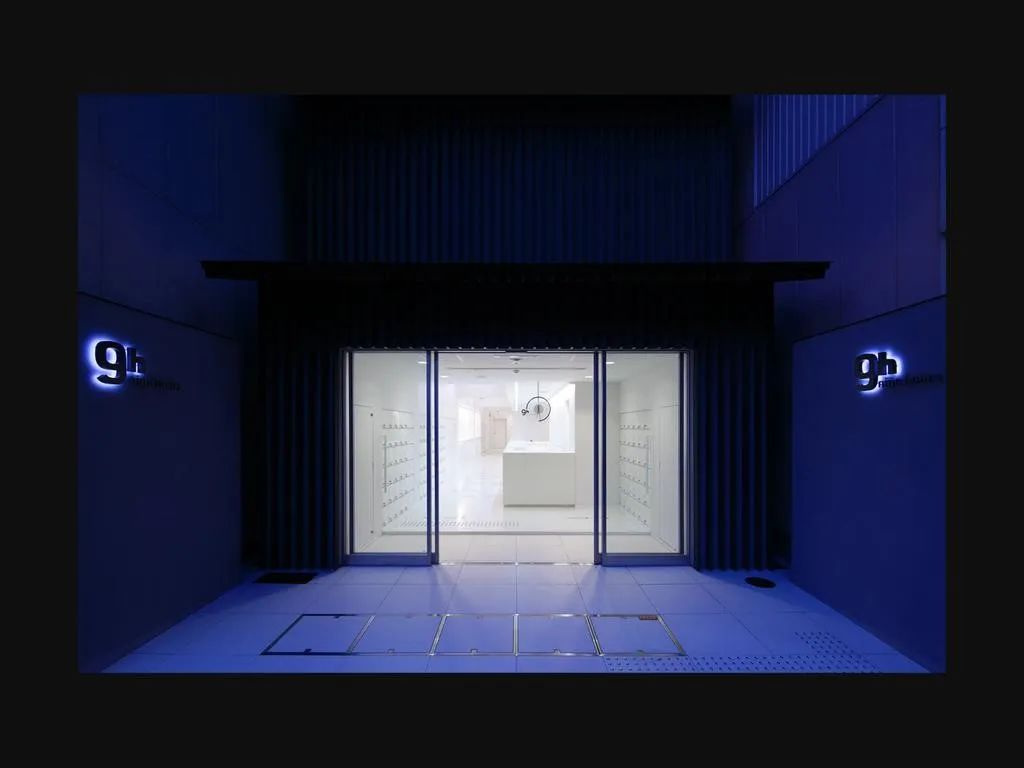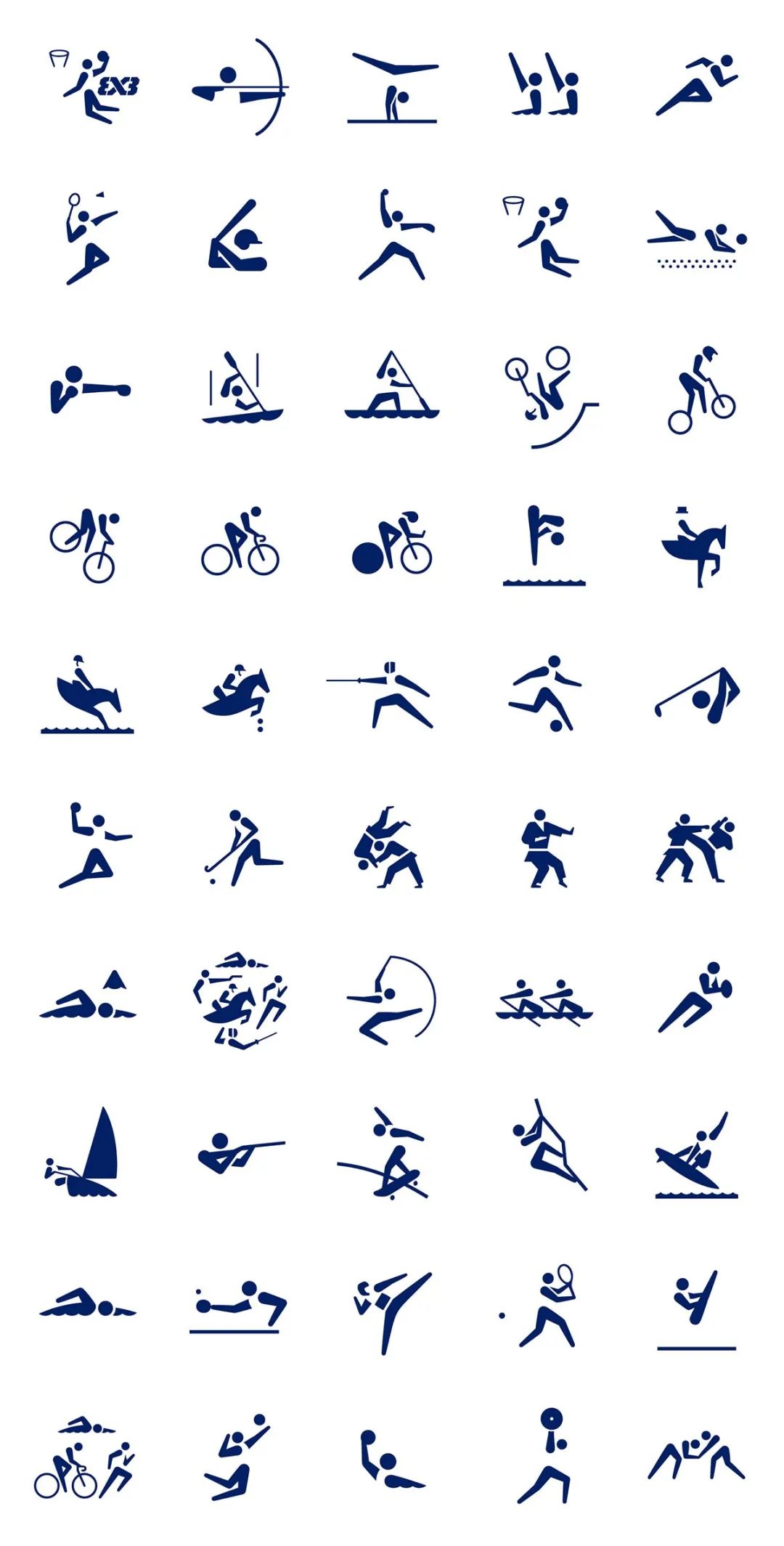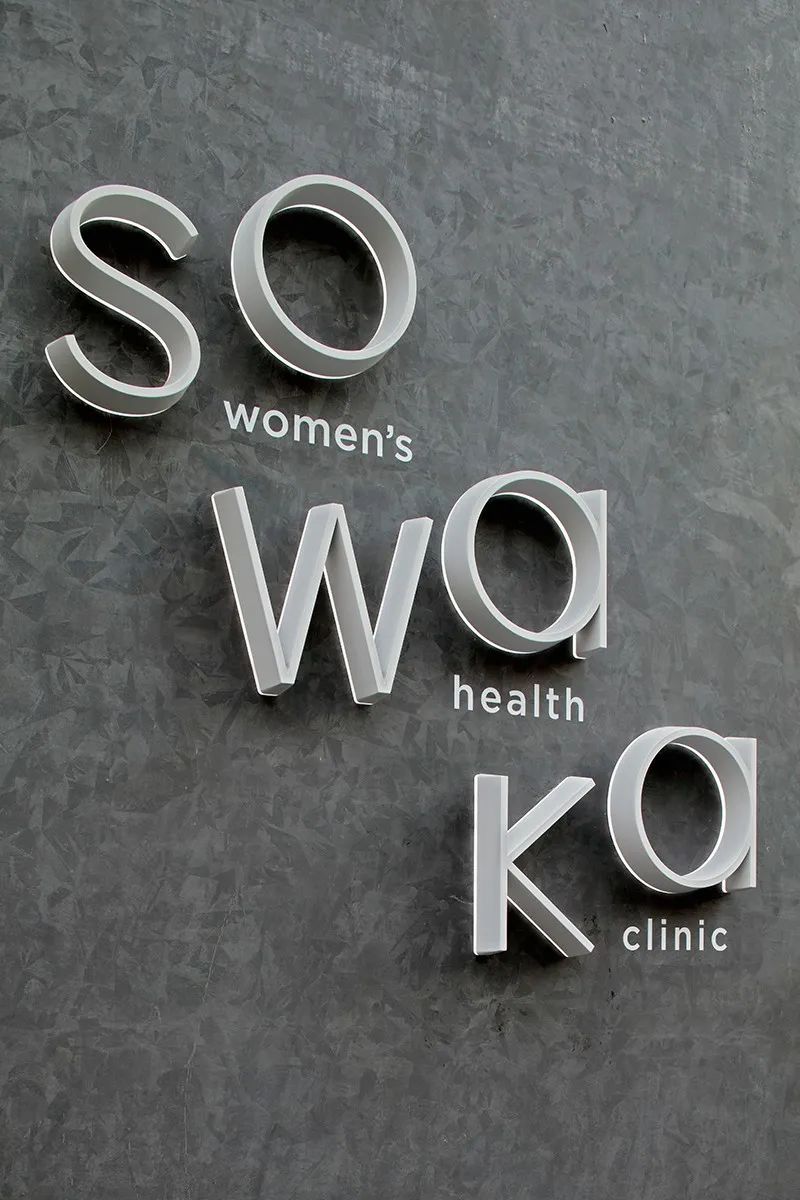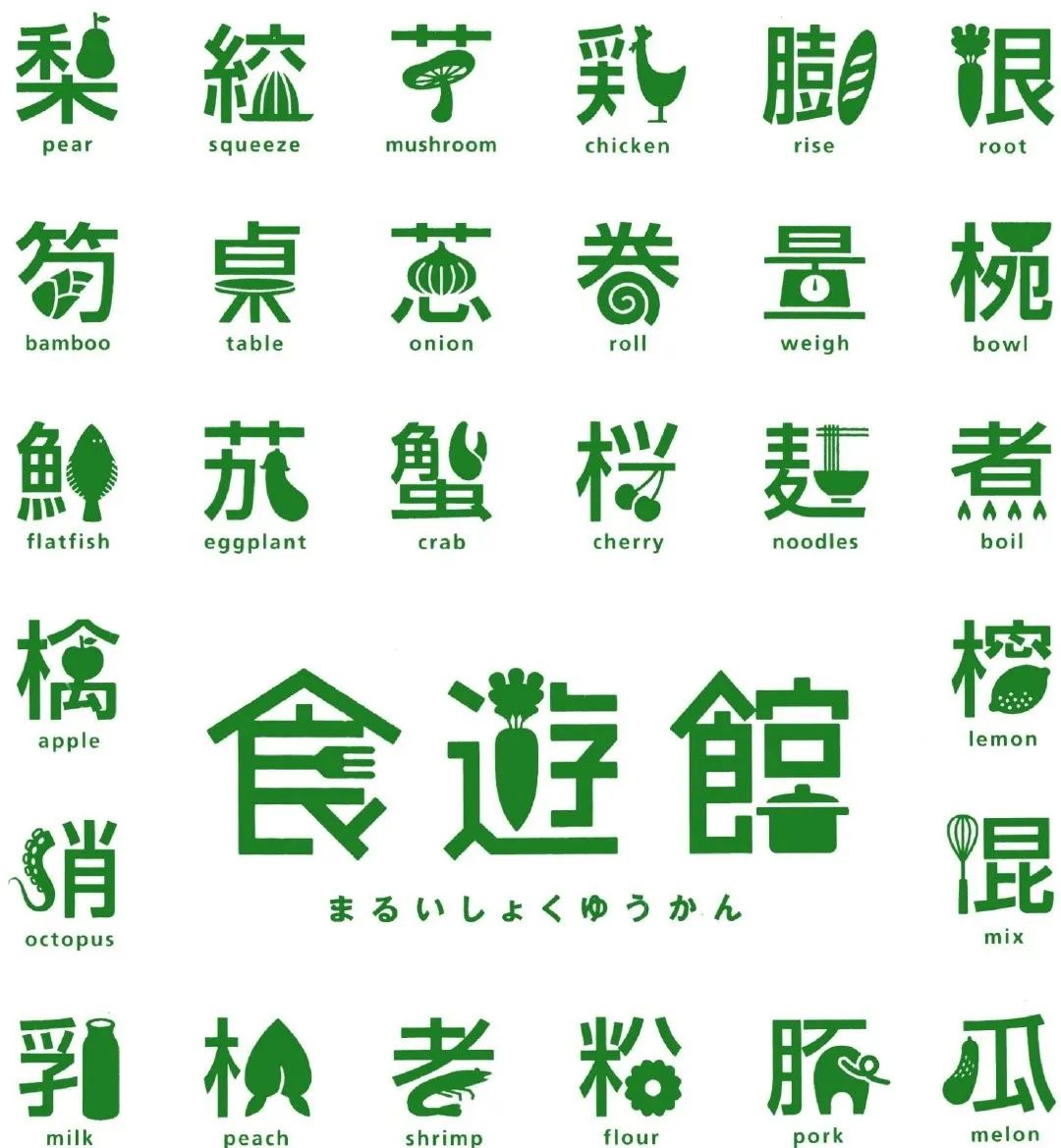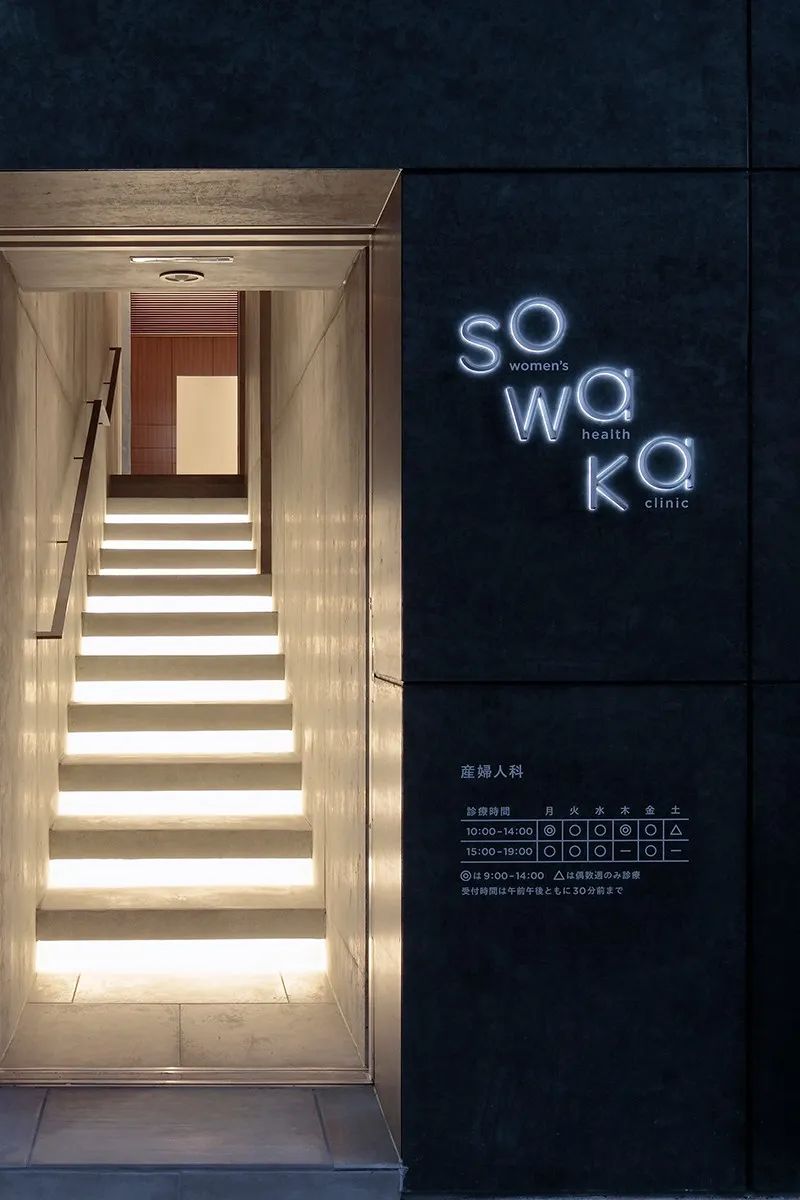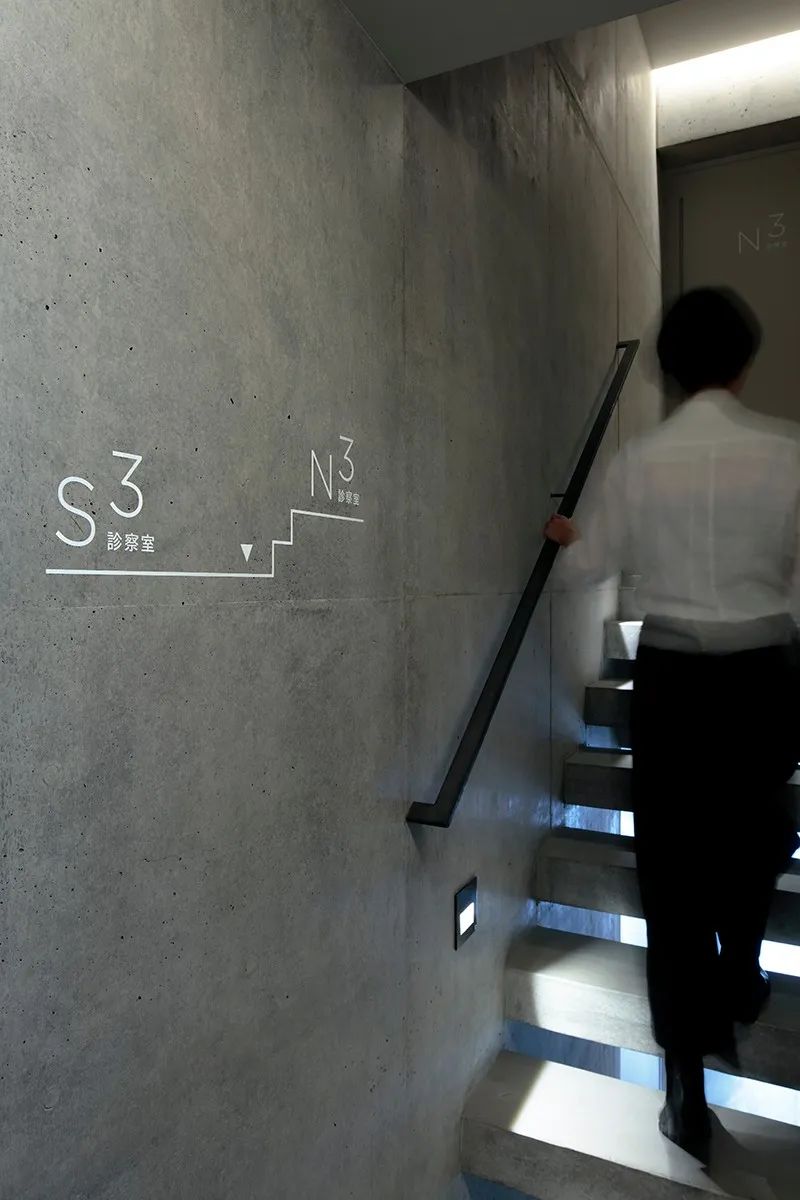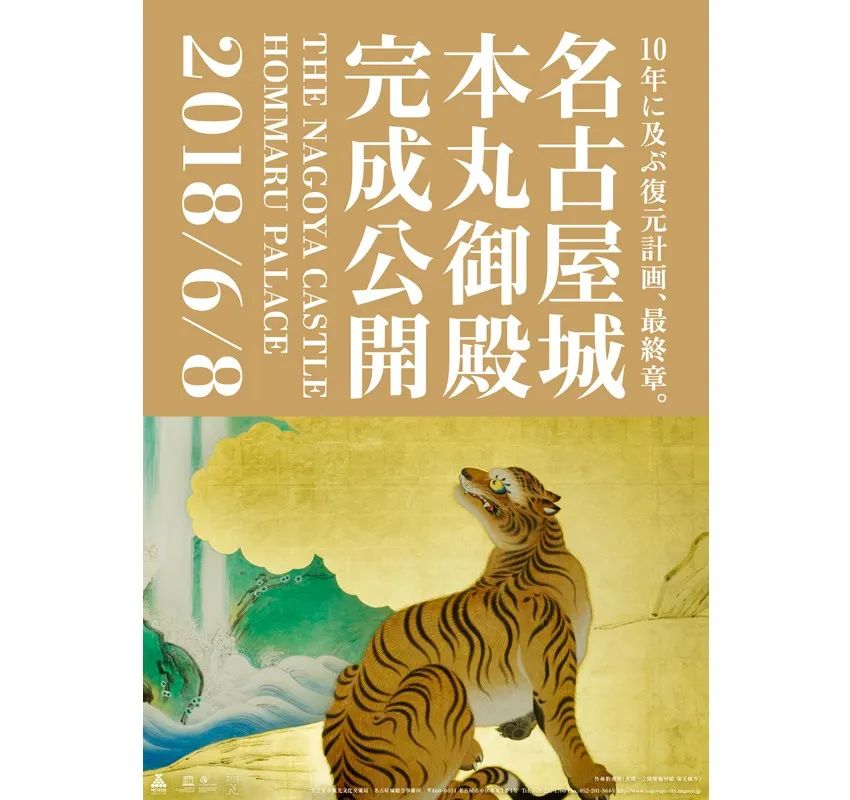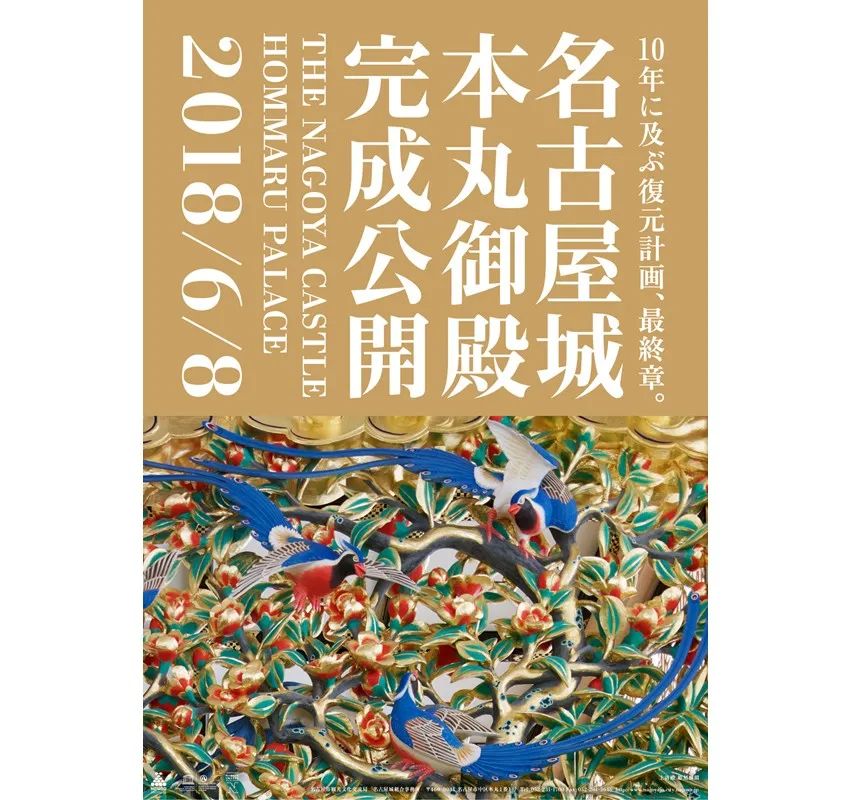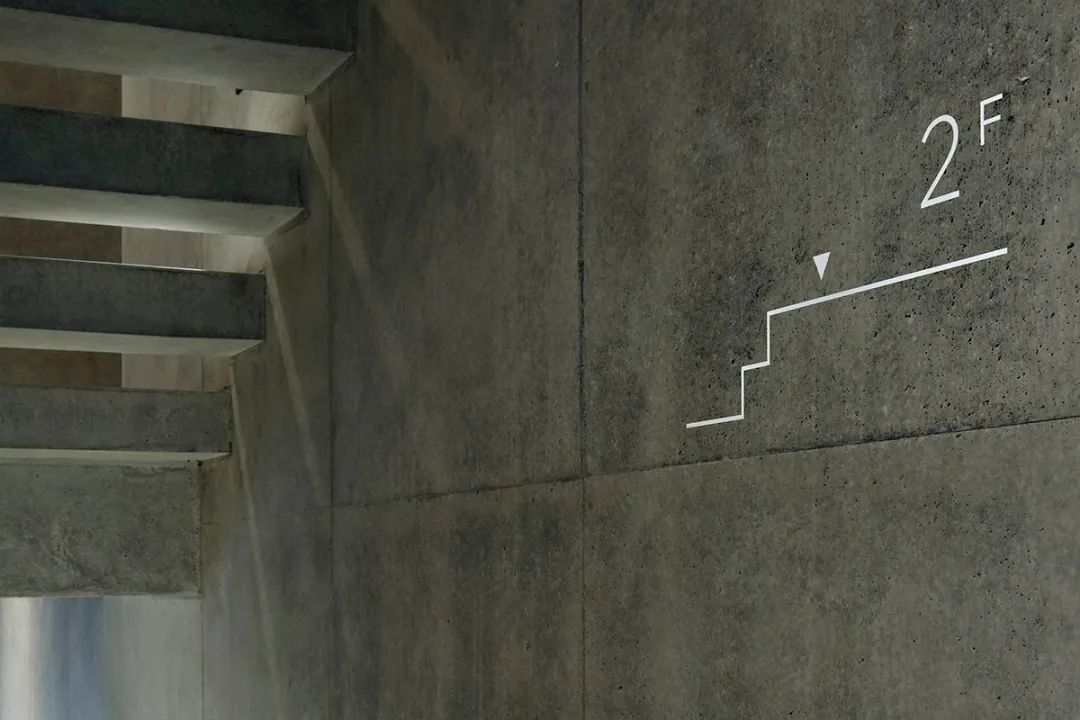
惊艳!东京奥运会73枚动态图标刷爆朋友圈
前不久,东京奥组委、残奥组委
公布了73个奥运比赛项目的动态图标
视觉效果堪称惊艳!
图标先以碎片的形式
从白色背景中出现
完成动作后又以碎片化形式消失
回到最初的空白帧
让人意犹未尽
没有一点多余的修饰
仅用最简洁的图形
就巧妙地传达出每项运动的特点
同时把运动员充满活力的姿态展现得栩栩如生
看得国内网友把彩虹屁吹上了天!
这73个动态图标中包括
33种奥林匹克运动项目
22种残奥会运动项目
日站君特意找出几个具有代表性的图标
供大家仔细欣赏
田径运动
空手道
滑板运动
竞技体操
花样游泳
羽毛球
射箭
击剑
橄榄球
残疾人网球
残疾人田径
残疾人射击
残疾人羽毛球
此次设计的图标分为两种类别
无框型与有框型
不仅线条简约
颜色也只选用蓝白两个色系
主色源于2020奥运会会徽的蓝色
也会一直以来日本国家队的代表色系
静态图标首次引入于1964年东京奥运
我们熟知的公共厕所门口上的小人儿
也诞生于那个时候
所以本次的动态图标
是东京这座城市
为奥林匹克贡献的又一个“第一”
东京奥运会的静态图标
由日本设计师广村正彰设计
于2019年3月正式公布
后由动态设计师井口皓太接手
进行动画效果的制作
历时一年设计才得以完成
那么这两位被奥组委钦点的设计师
到底什么来头?
下面日站君就为大家郑重介绍一下!
01
广村正彰
引领着日本设计界传统精神的再造
广村正彰,日本著名设计师
作品涉及导视设计、平面设计、
书籍设计、包装设计等诸多领域
代表作有京都9小时胶囊旅馆、丸井北千住食遊館等
国内的天津图书馆导视设计、
建外 SOHO 北京标识系统
也是他的作品
武藏野美术大学毕业后
广村正彰进入田中一光事务所工作
十一年后,才成立了个人的设计工作室
Hiromura Design Office
先后斩获过JAGDA新人奖、
N.Y. ADC奖、SDA奖、JCD奖等不少设计界荣誉
说到他的京都9小时胶囊旅馆导视设计
你也许不会陌生
京都9小时胶囊旅馆的定义是
1小时洗漱,7小时睡眠,1小时休息
倡导最大程度简化旅人的生活模式
因此在处理导视系统时
广村正彰也选择了简洁克制的视觉形态
他将入住程序划分为四个步骤
咨询前台、索取房间钥匙、淋浴、进入胶囊房间
并以简明的图标表现在空间当中
这样一来,不管办理住宿手续
还是寻找房间号
住客通过墙壁、地面上醒目的图标和箭头
就能迅速有序地解决问题
在保持直观的视觉效果外
广村正彰更讲究设计质感的呈现
司空见惯的数字在他的手下
呈现出别样的新秩序
在光影的衬托中
数字得到立体映现
散发着现代却又不失古朴的视觉美感
2004年,他为丸井北千住食游馆打造品牌形象时
设计的字体《丸井 北千住 食遊館》
也让人印象深刻
这套设计图文并茂
既是文字,也是装饰图案
手法虽然不新鲜
但却结合得非常巧妙,趣味十足
其他部分作品赏析
《コスメロフト 東急プラザ表参道原宿》
《sowaka women’s health clinic》
《名古屋城本丸御殿 完成公開》
《鉄道博物館》
02
井口裕太
80后新生代动态设计师中的全能王
另一位男主角井口皓太
则以动态设计为主
在平面、影像、空间、网页等设计领域均有涉猎
从动态图形到写实影像导演无一不通
尤其擅长创意指导
尽管还是一名80后年轻设计师
却也已获2014东京TDC奖、
D&AD 2015 yelllow pencil、
NY ADC奖2015 goold 等多项大奖
这个名为“無限に続く道と漢字”的GIF动画系列
(无限中的深巷与汉字)
曾让不少国内设计师为之拍案叫绝
“布”
“间”
他别具匠心地将汉字与立体空间相融合
同时加入动画元素
空间的纵深感与无限循环所带来的感官体验
让人回味无穷
不失为传统文化与现代艺术
一次很棒的尝试
“伞”
“京”
“门”
“竹”
近看是“木”,远看又成“林”
设计师其他作品赏析
《CI_clock PLST》
《NIKE 2020》
《CI_clock GU》
通过东京奥组委的这次动作
可以看出日本为了这次奥运会
还是花费了巨大心力的